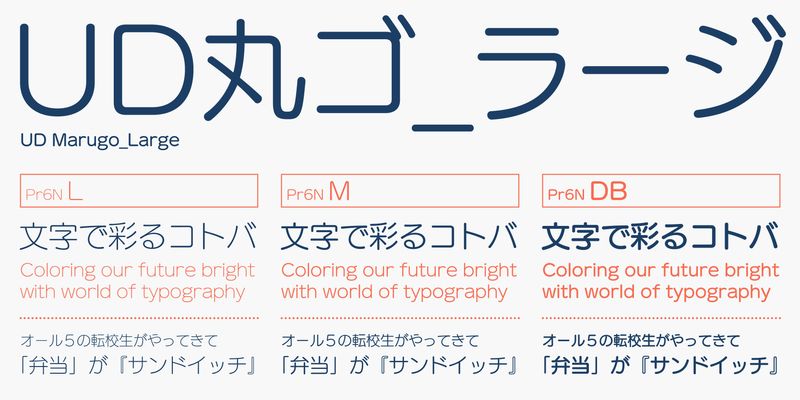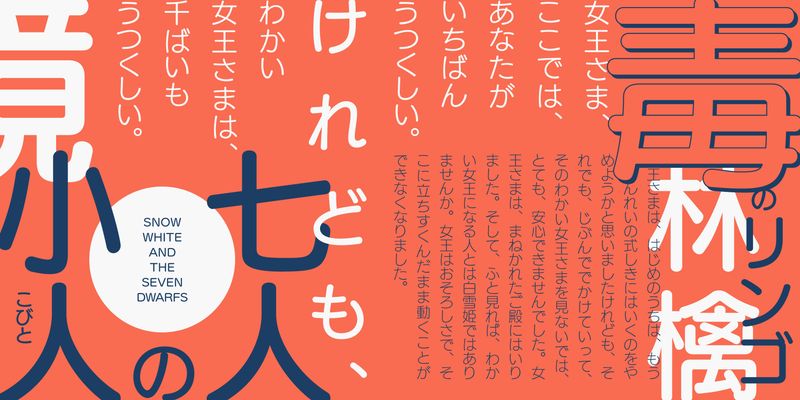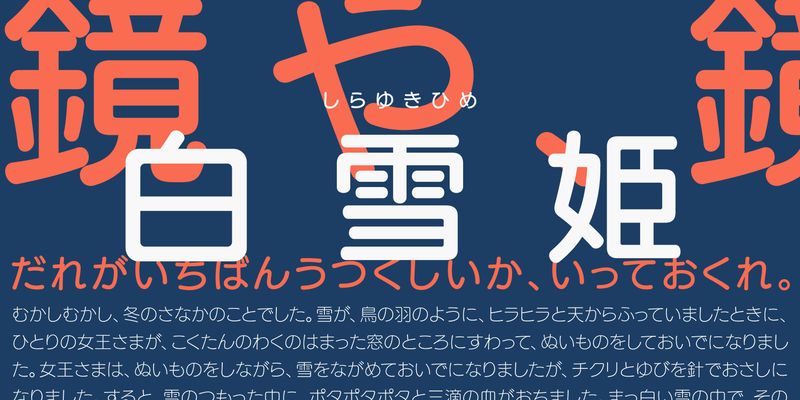
FOT-UDMarugo Large Pr6N basiert auf dem Design der hochgelobten Schrift „Seurat”, verfügt jedoch über vergrößerte Kana- und alphanumerische Zeichen, um ein abgerundetes serifenloses Schriftbild mit einem moderneren Stil zu schaffen. Zusätzliche subtile Anpassungen verbessern die Sichtbarkeit und Lesbarkeit des Schriftbildes.